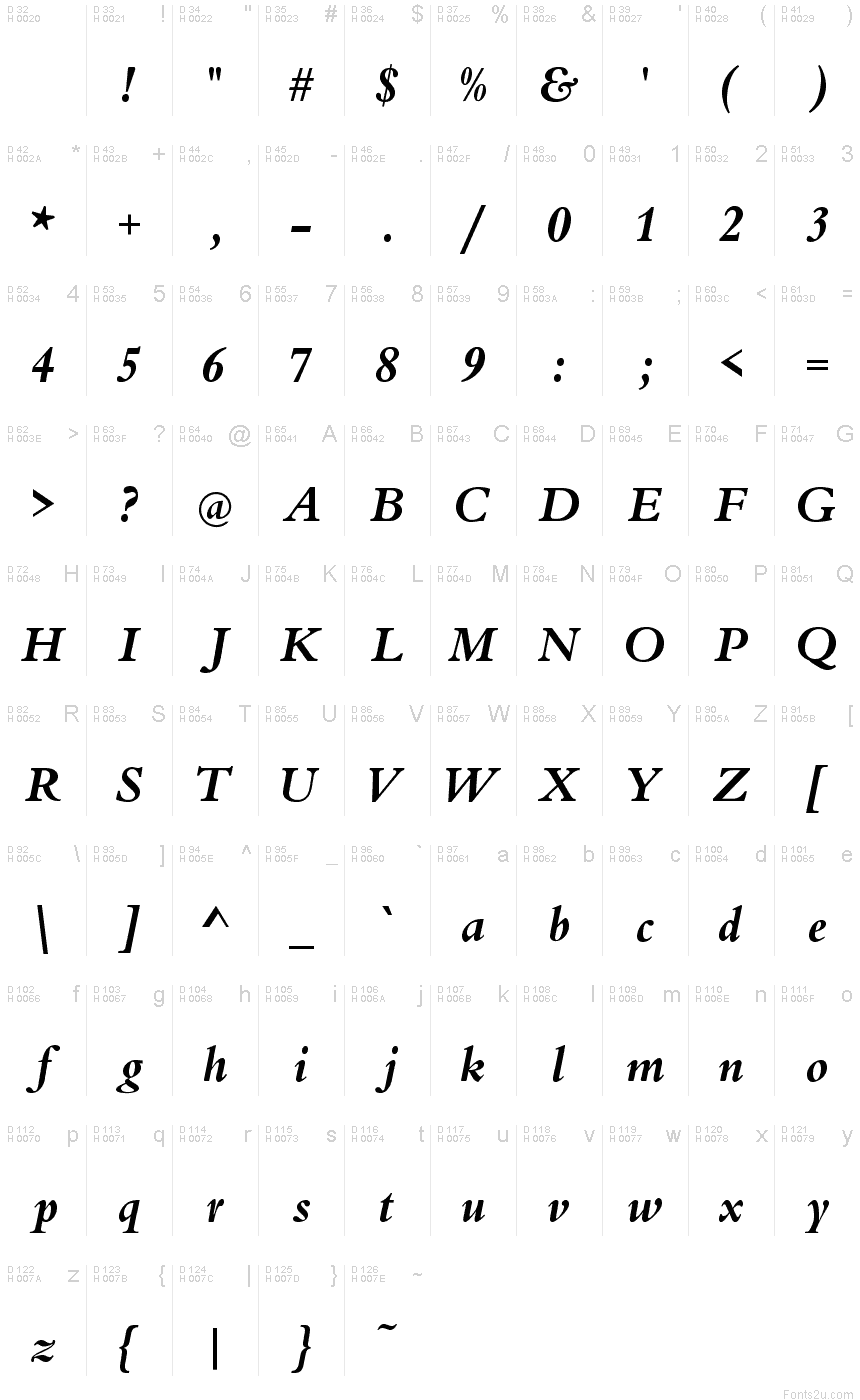
BergamoStd-BoldItalic
Bergamo Std Bold Italic è un carattere serif corsivo gratuito dal sapore classico e squisitamente letterario. Le lettere si inclinano con sicurezza, abbinando tratti scuri e decisi a grazie morbide e a qualche vivace guizzo calligrafico, particolarmente evidente nelle minuscole arrotondate e nella coda fluida della g.
Si presta perfettamente al branding editoriale, alle copertine di riviste, ai poster letterari, al packaging e ai menu di ristoranti in cui un tono europeo classico aiuta a veicolare il messaggio. Essendo un font gratuito, è l'ideale anche per titoli, citazioni e brevi intestazioni, poiché le sue curve generose e il ritmo inclinato donano anche alle parole più brevi una presenza colta e leggermente drammatica.